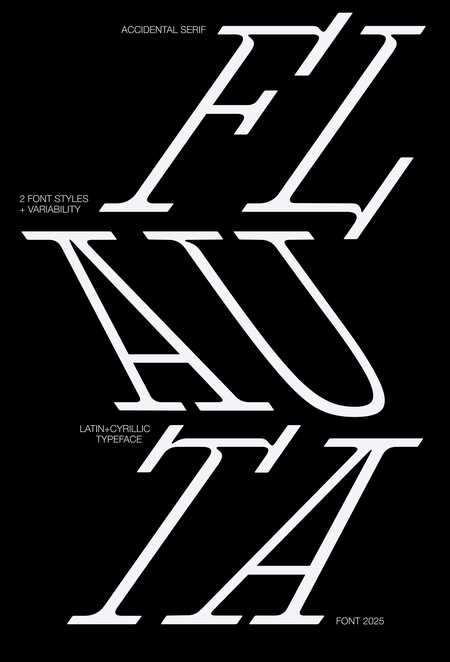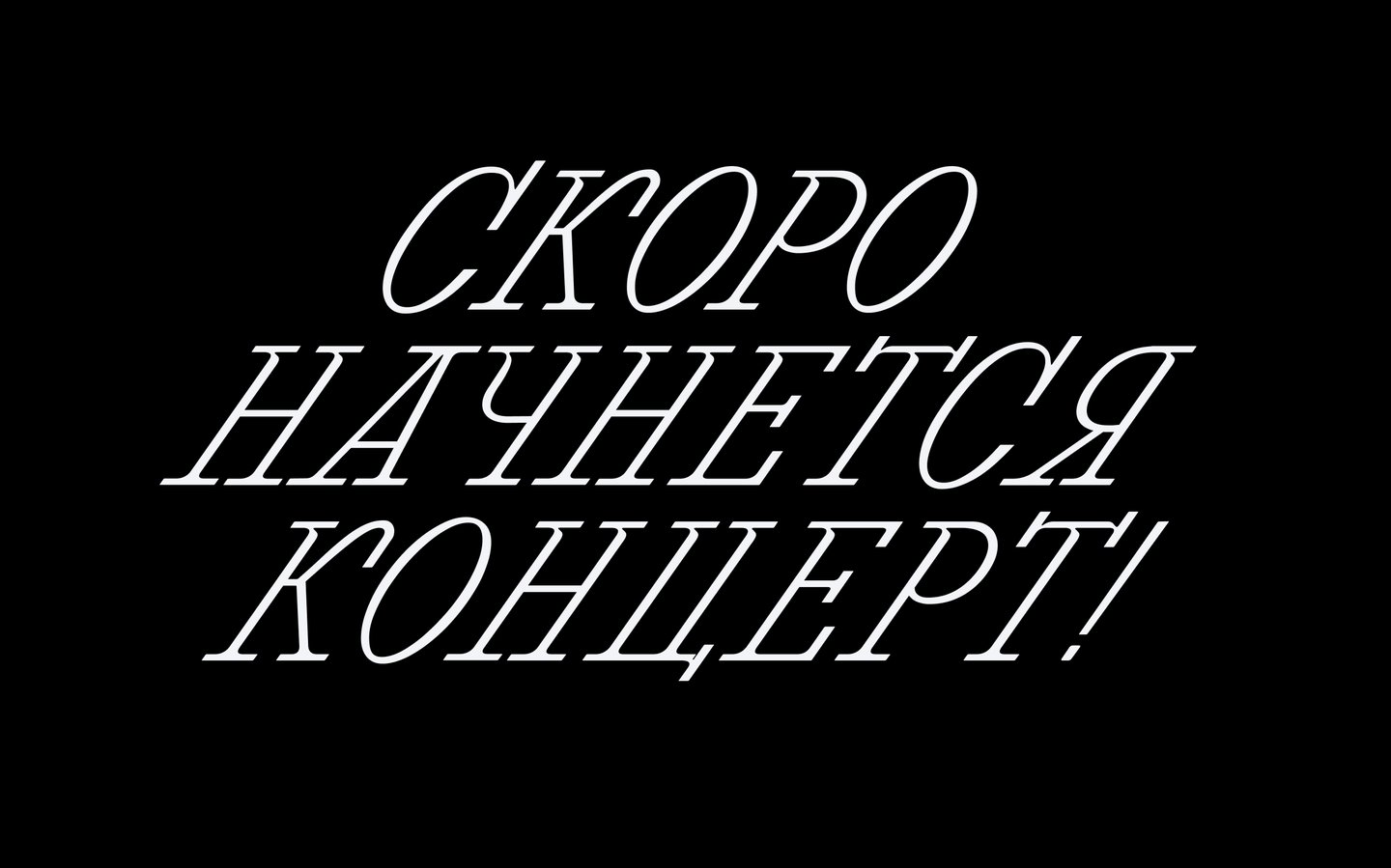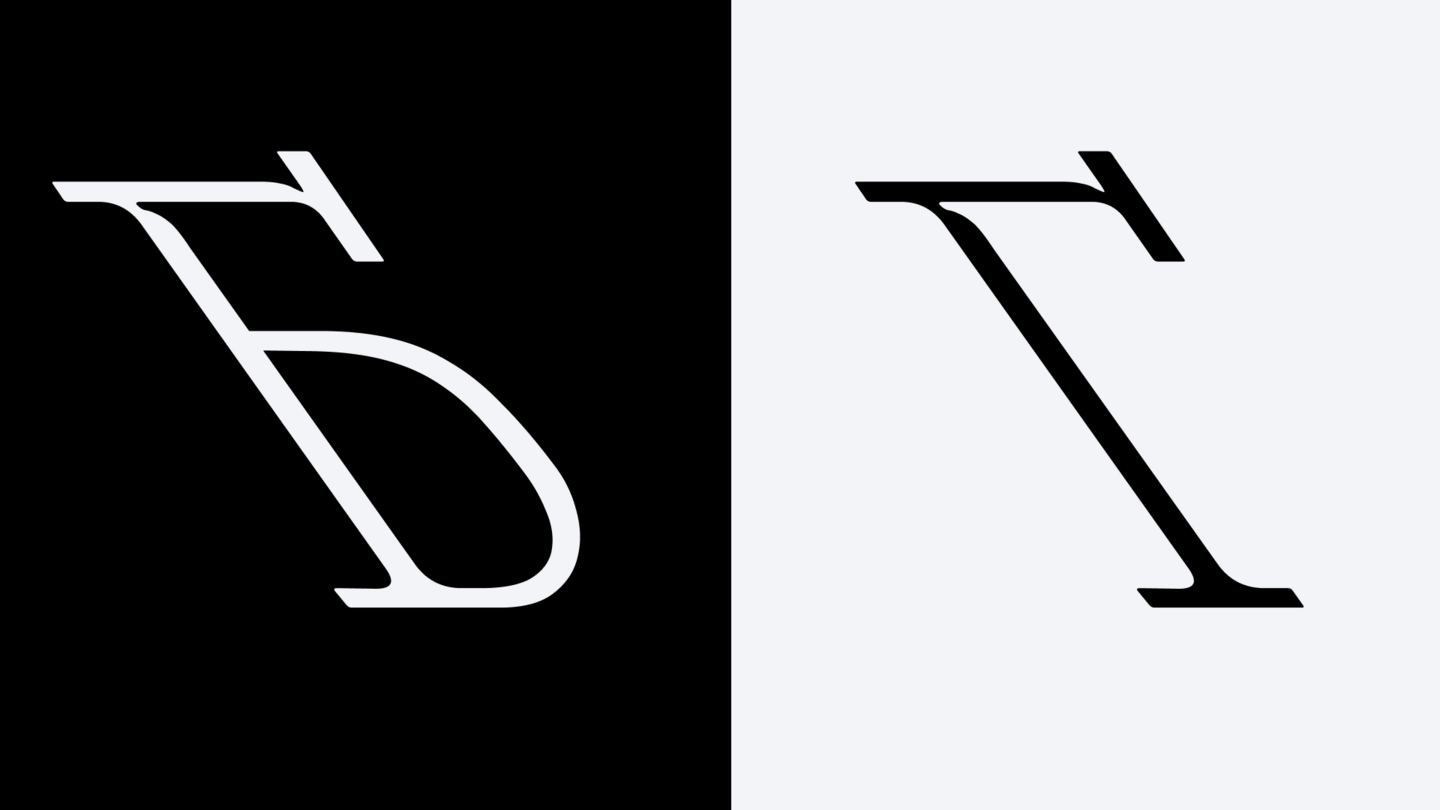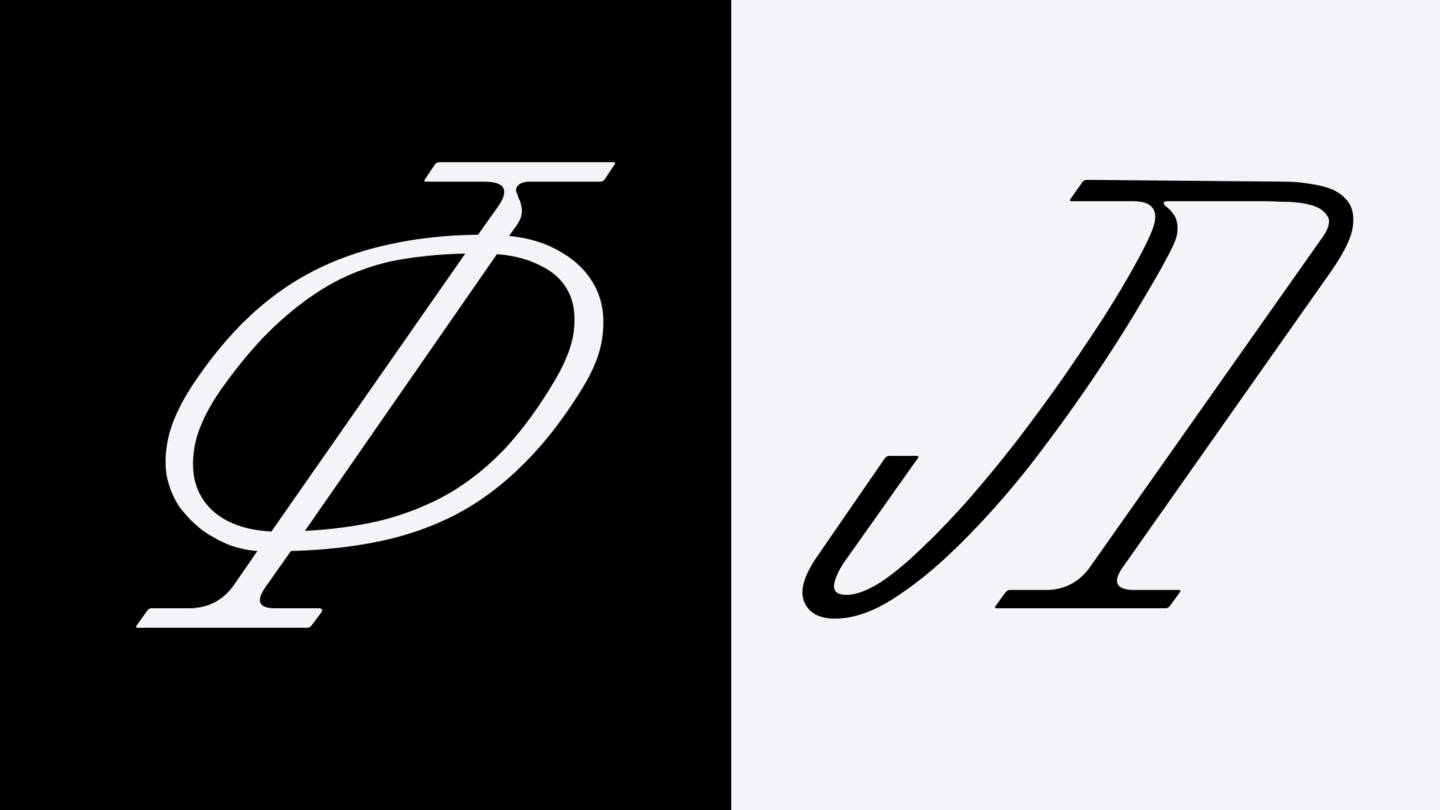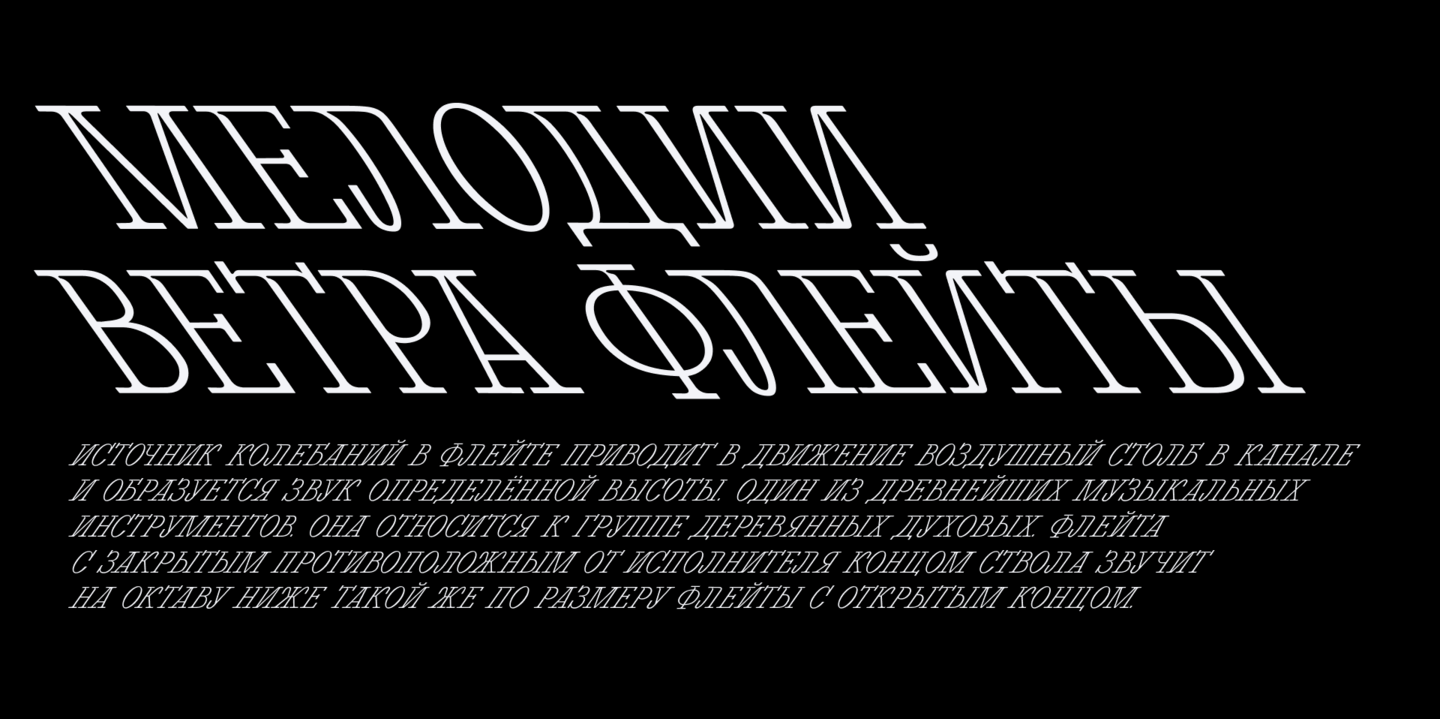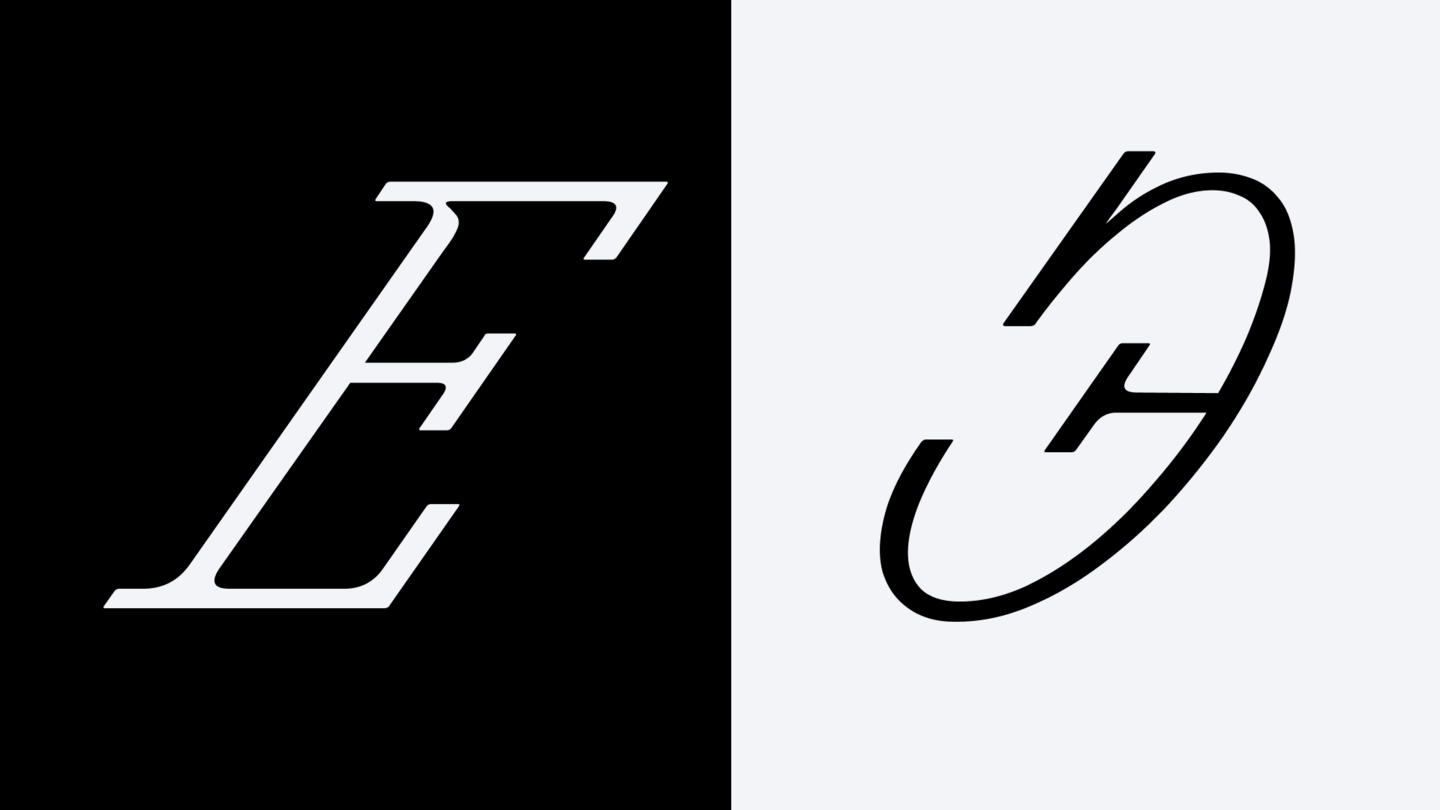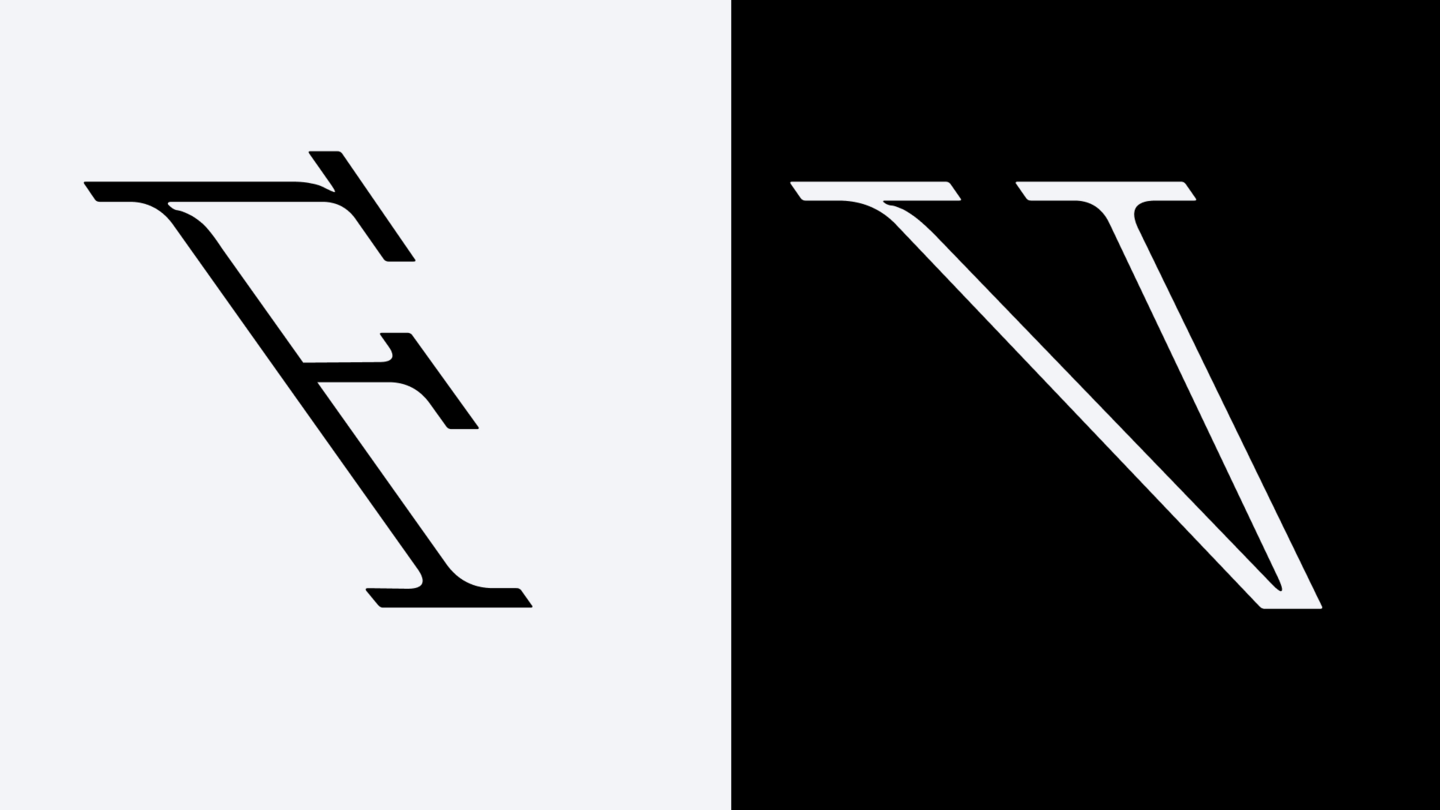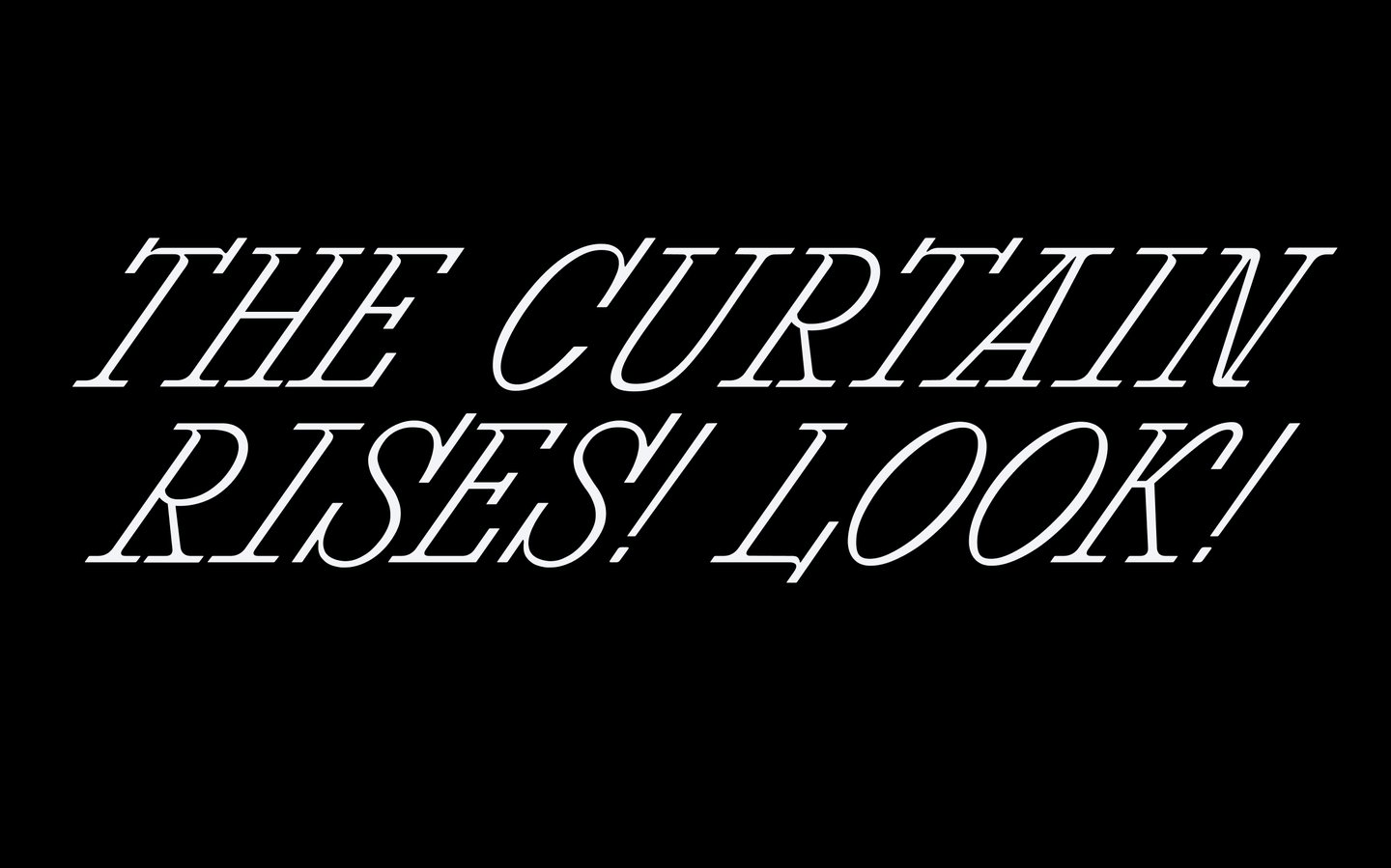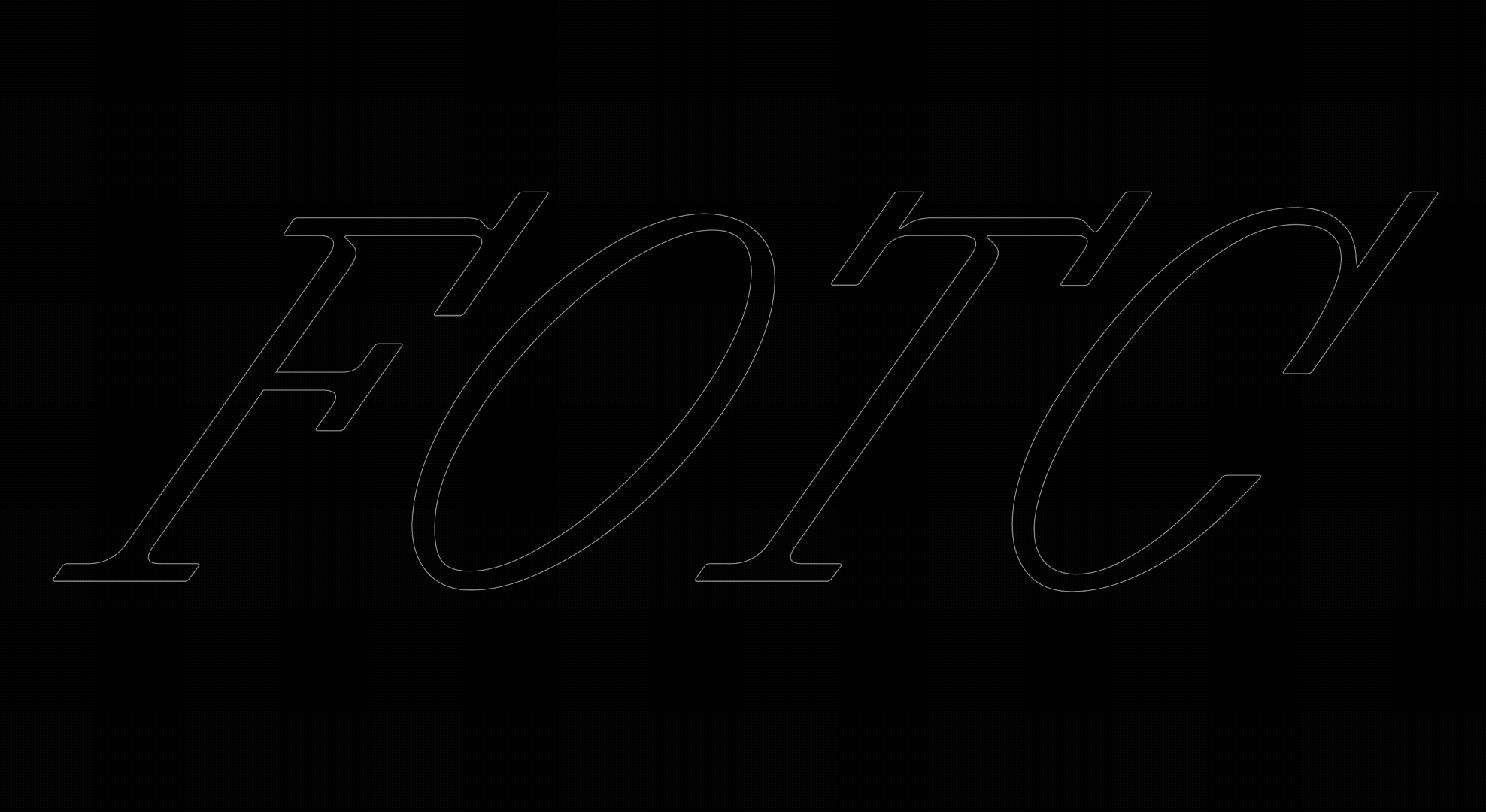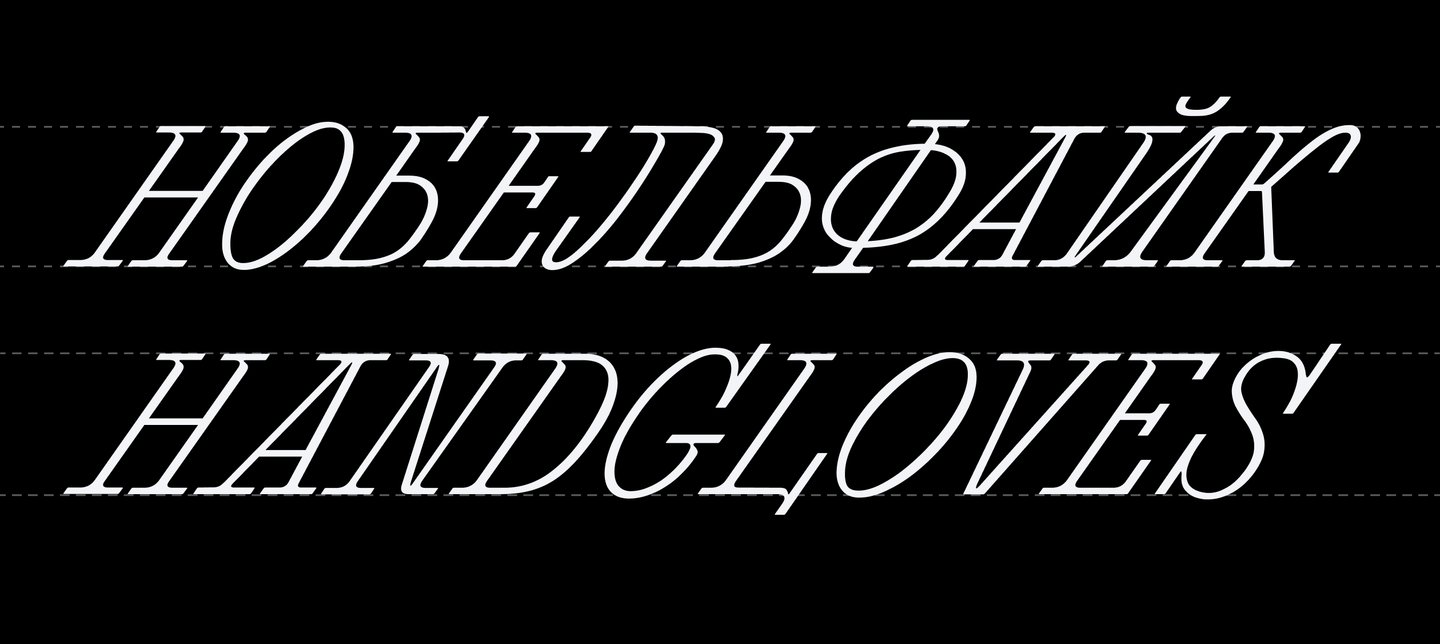
Flauta — это акцидентная вариативная антиква, вдохновлённая движением ветра и звучанием духовых инструментов.
Шрифт имеет два начертания — Italic и Retalic, а также поддерживает вариативность и лучше всего раскрывается в заголовках и крупном наборе.
Полная касса включает в себя кириллический и латинские алфавиты, цифры и пунктуационные знаки.